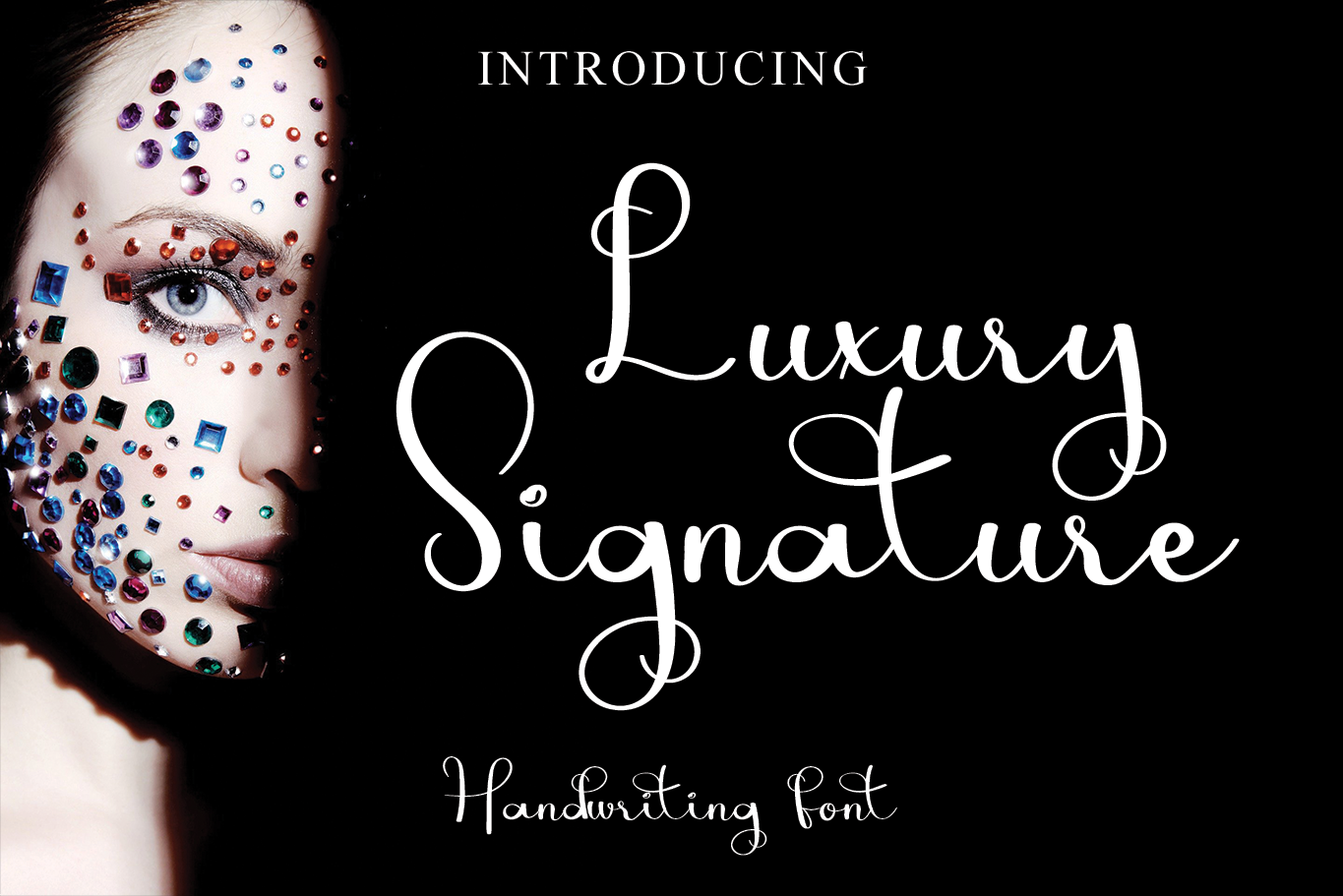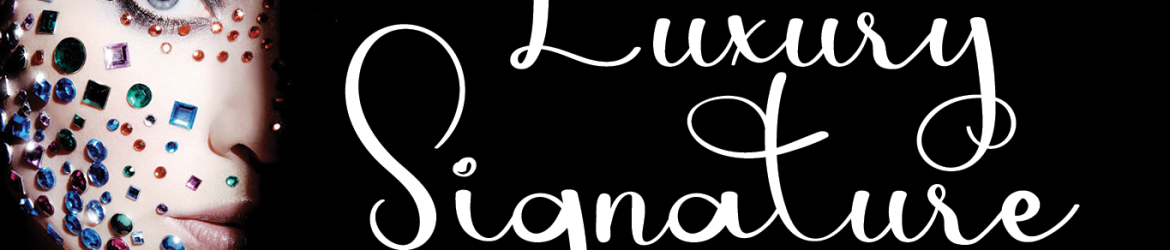
Luxury Signature Font – Download Grátis
Esta é uma fonte script elegante, com traços finos e escrita cursiva. É perfeitamente cuidadosamente feita, repleta de detalhes. Ainda que qualquer tópico seja abordado, essa font será um excelente ativo para sua coleção de fonts, pois tem a capacidade única de adicionar brilho a qualquer criação. Com sua textura delicada e traços finos, a ‘Luxury Signature Font’ do designer Erik Studio não apenas adicionará um toque sofisticado a qualquer design, mas também o transformará em algo único. Este script elegante é perfeito para incorporar em materiais de luxo ou criações que exigem um certo refinamento e estilo pessoal. Englobando desde assinaturas de negócios até cartões de visita, esta font será uma escolha sólida para aqueles buscando uma identidade visual atraente e única.